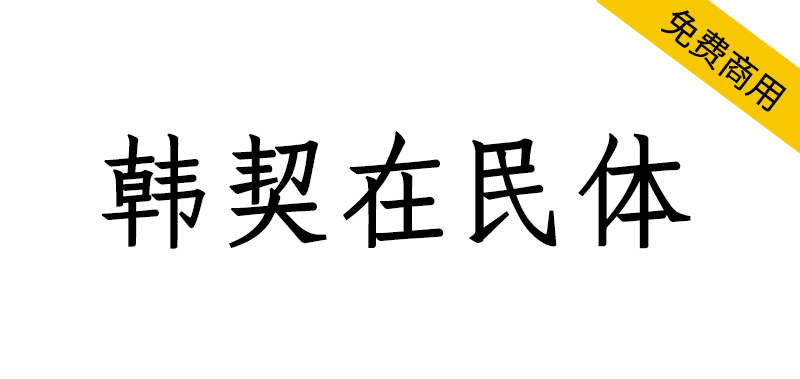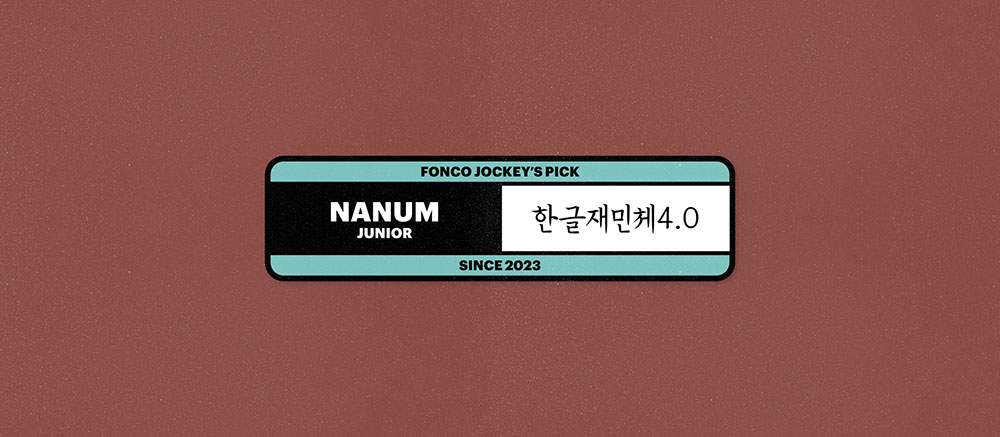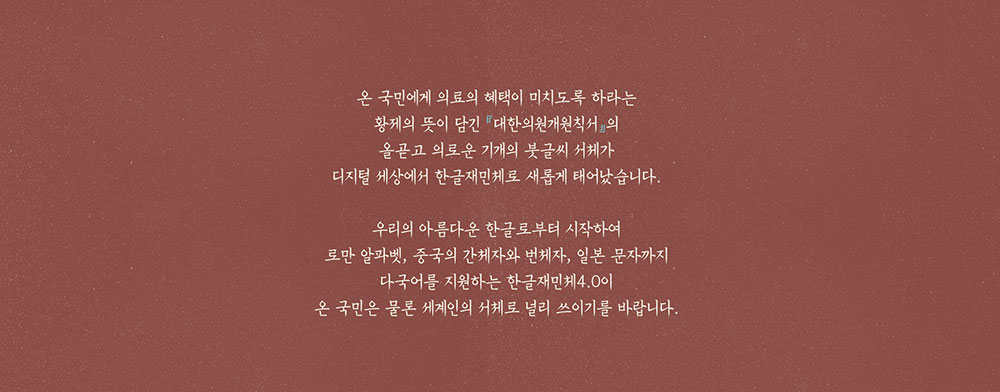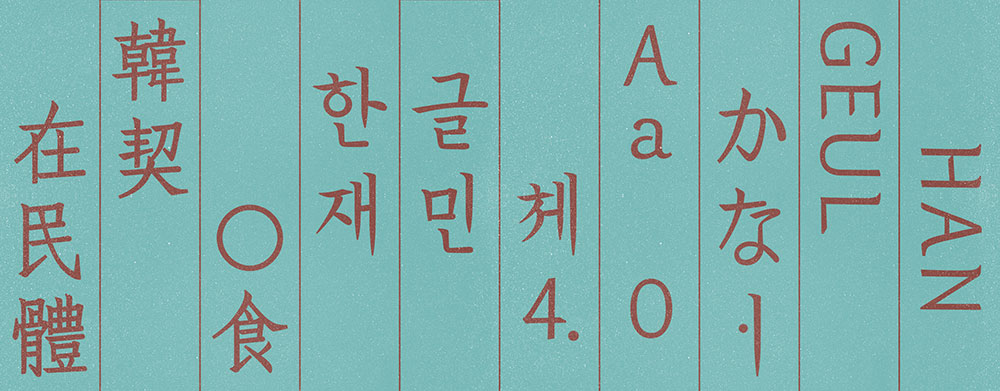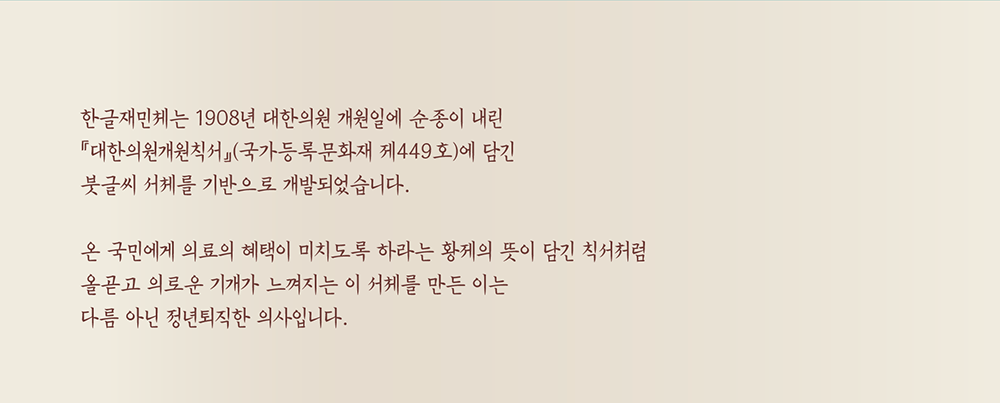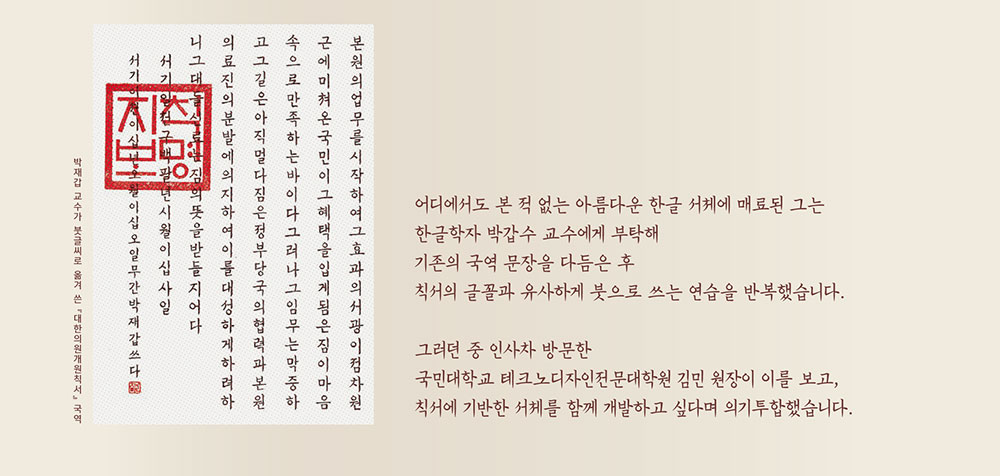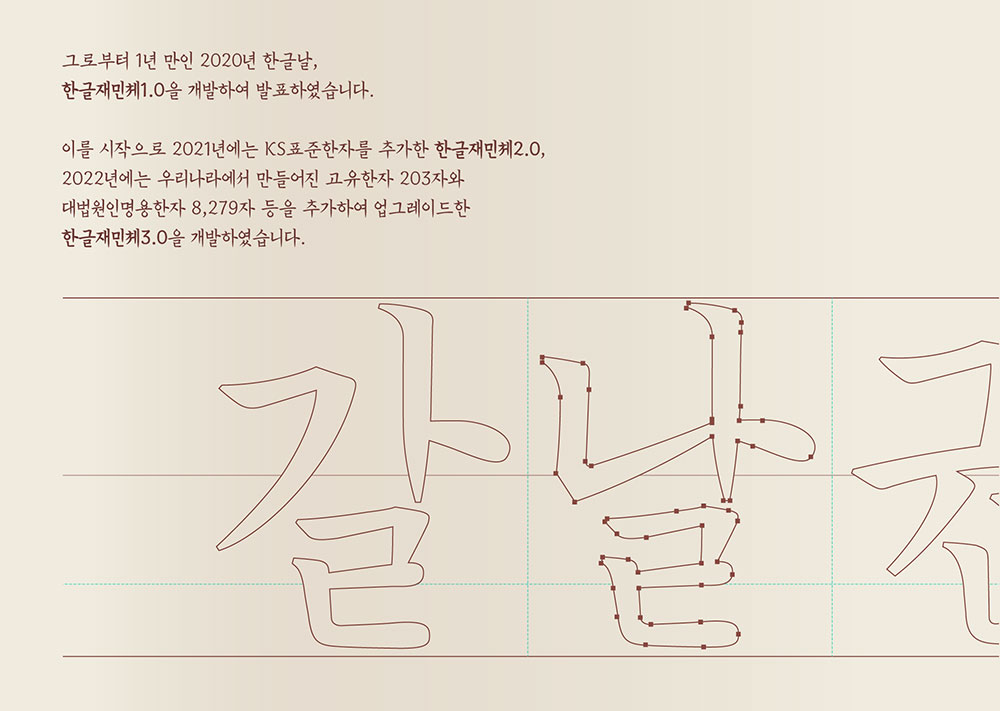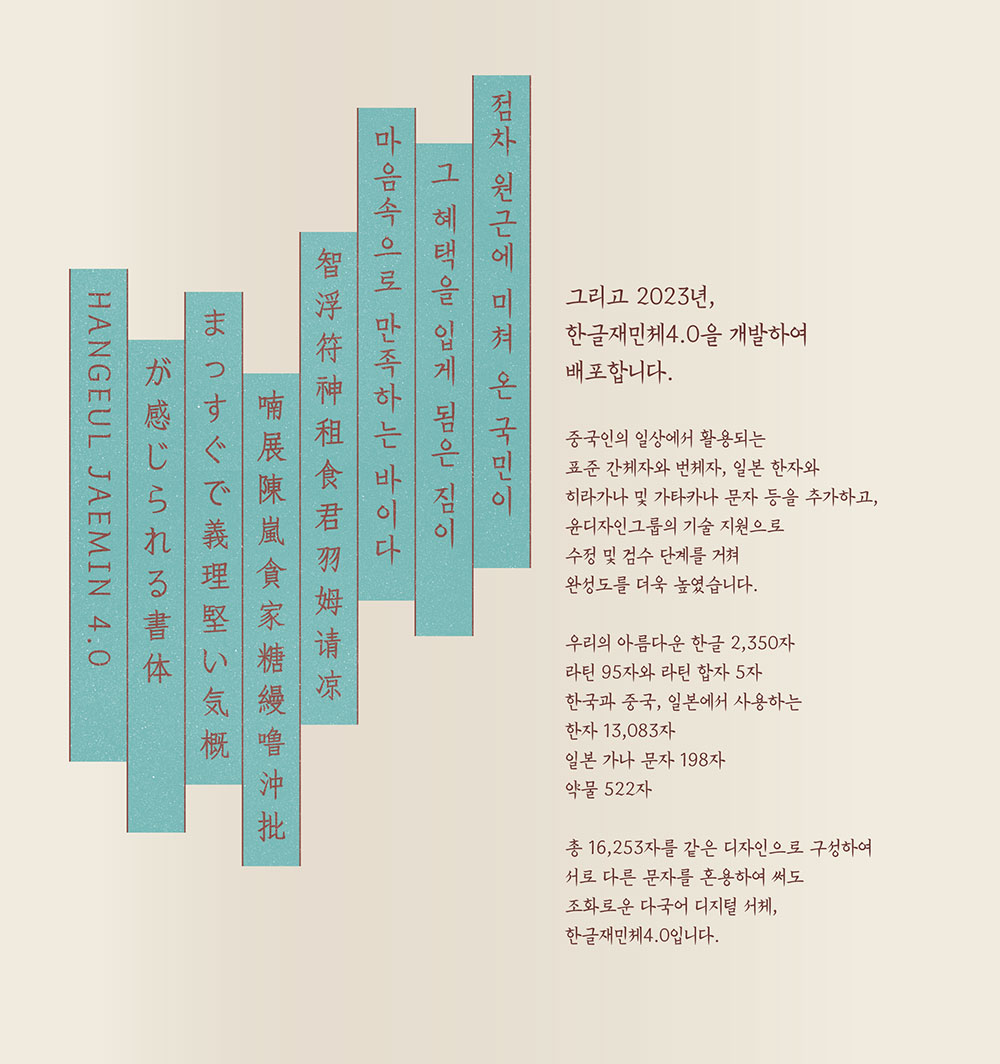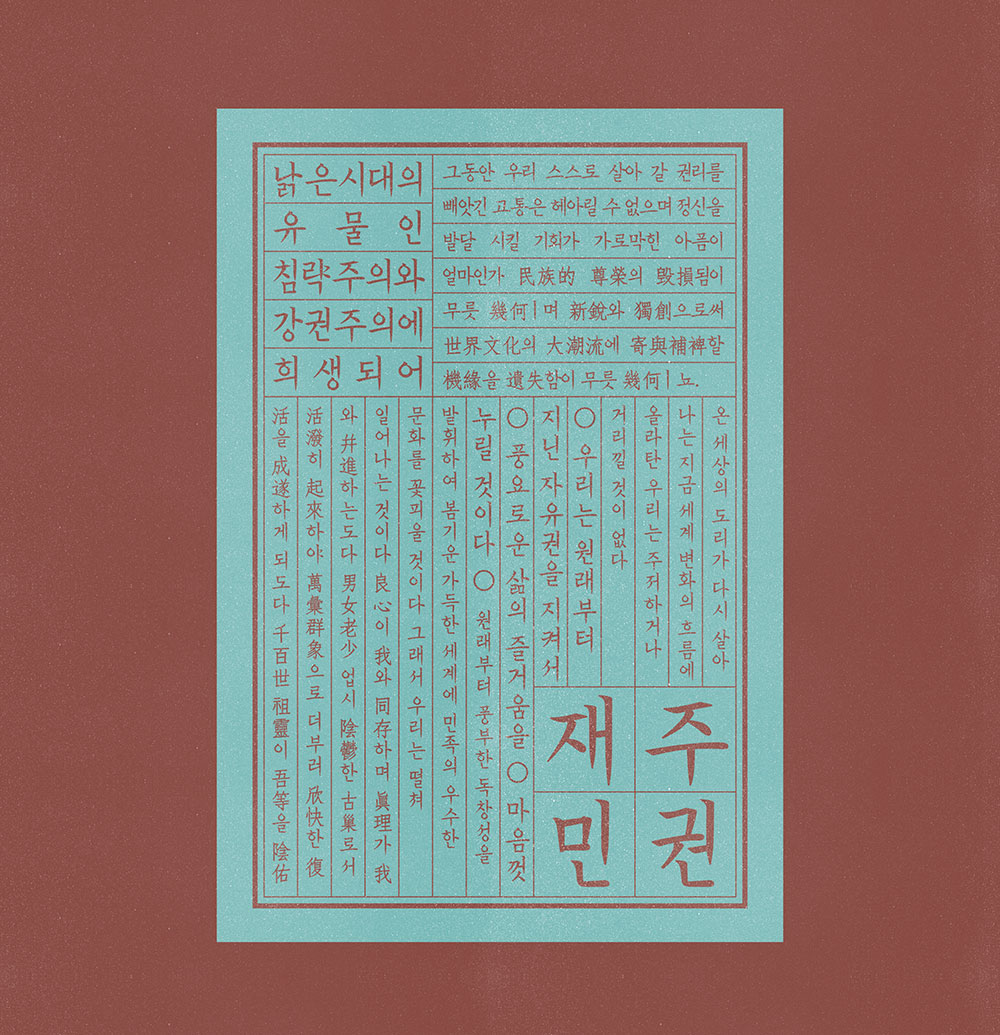
韩契在民体(韩文名:한글재민체,英文名:hangeul jaemin)是以1908年颁布的《大韩国会开幕原则书》(国家注册文化财第449号)中的毛笔书法字体为基础,由朴载甲前首尔大学医学院教授和金敏国民大学技术设计专门大学院院长共同开发。2020年在韩文字日发布了韩契在民体1.0,2021年增加了KS标准汉字的韩契在民体2.0,2022年又增加了韩国独有的203个汉字和大法院人名用8289个汉字等,发布了升级版的韩契在民体3.0。而由尹设计集团(윤디자인그룹)于2023年发布的韩契在民体4.0,增加了中国人日常使用的标准简体字和繁体字、日本汉字以及平假名和片假名等。至此,韩文和拉丁字母、中国简体字和繁体字、日本文字也由相同的设计组成,完成了支持多种语言的数字字体。
한글재민체는 1908년 대한의원 개원일에 순종이 내린 『대한의원개원칙서』(국가등록문화재 제449호)에 담긴 붓글씨 서체에 기반을 두고 박재갑 전 서울대학교 의과대학 교수와 김민 국민대학교 테크노디자인전문대학원 원장이 함께 개발하였다. 2020년 한글날에 발표한 한글재민체1.0을 시작으로 2021년에는 KS표준한자를 추가한 한글재민체2.0, 2022년에는 우리나라에서 만들어진 고유한자 203자와 대법원인명용한자 8,279자 등을 추가하여 업그레이드한 한글재민체3.0을 발표하였다. 그리고 2023년 윤디자인그룹을 통해 배포하는 한글재민체4.0은 중국인의 일상에서 활용되는 표준 간체자와 번체자, 일본 한자와 히라가나 및 가타카나 문자 등을 추가하였다. 이로써 한글과 로만 알파벳, 중국의 간체자와 번체자, 일본 문자까지 같은 디자인으로 구성하여 다국어를 지원하는 디지털 폰트를 완성하였다.